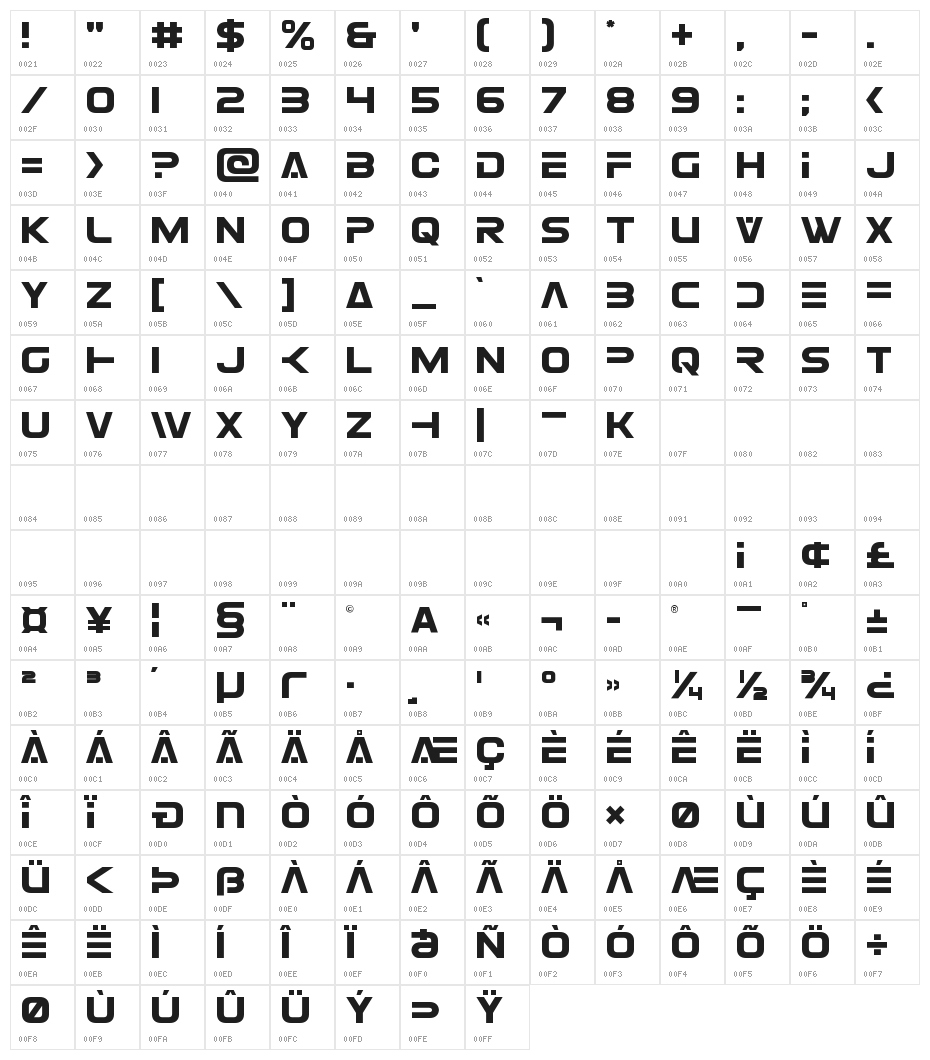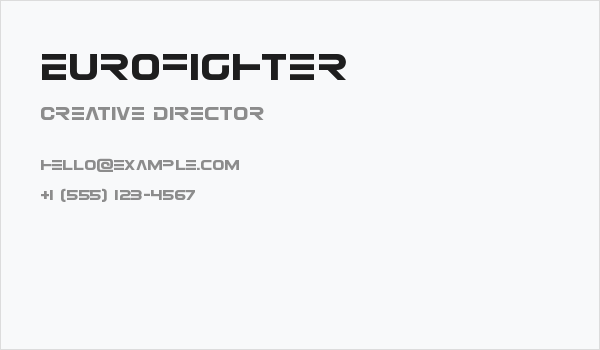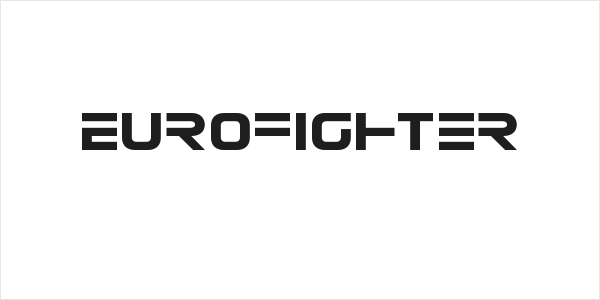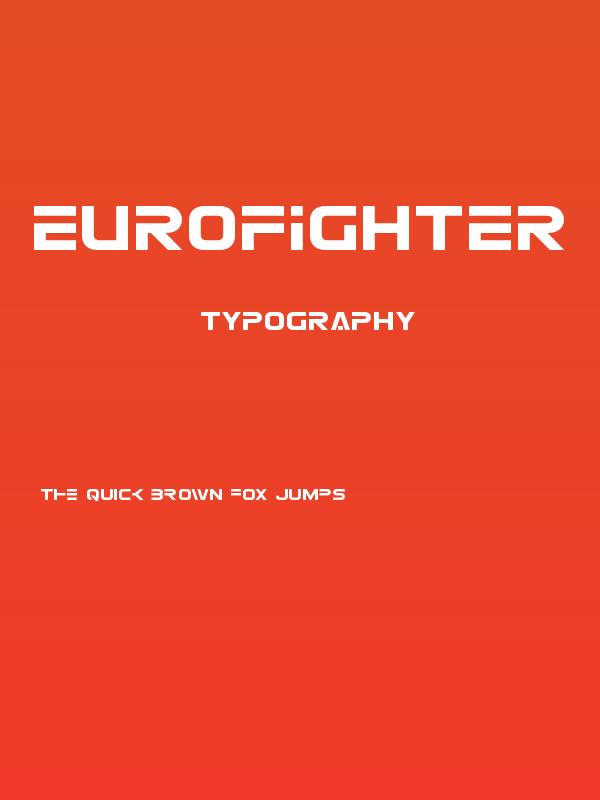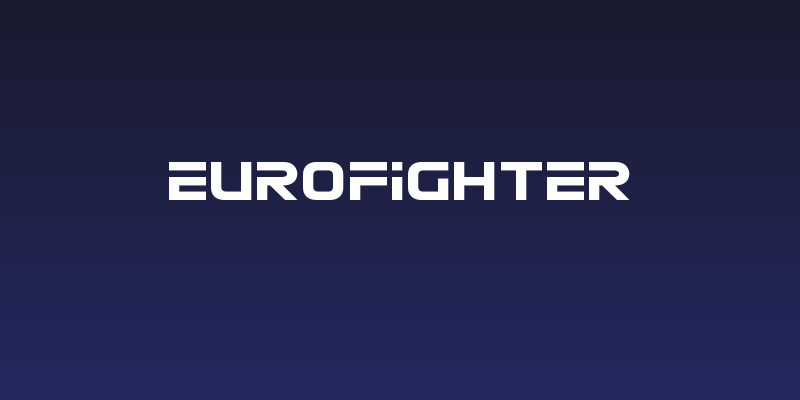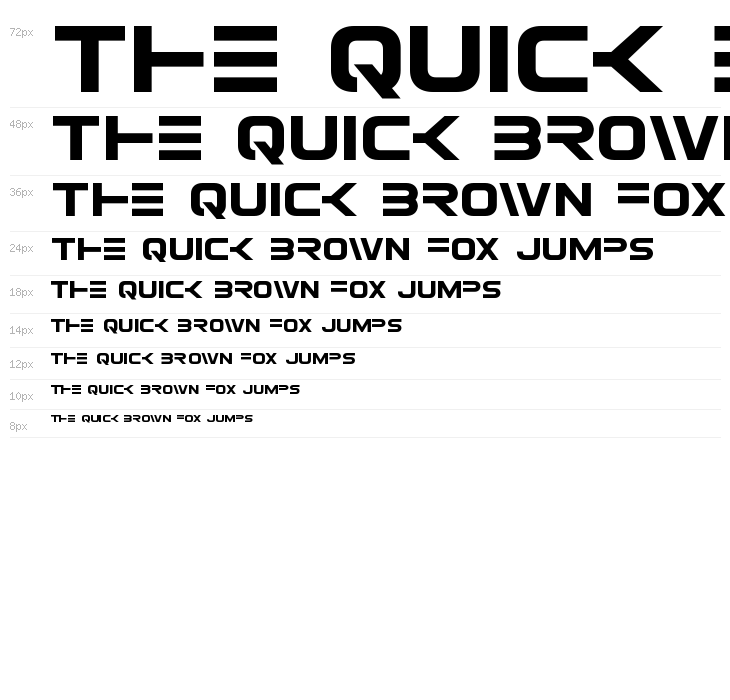
Eurofighter Font
| Vorgeschlagene Projekte | Ideal for technology branding, video game titles, sci-fi movie posters, and modern advertising campaigns. |